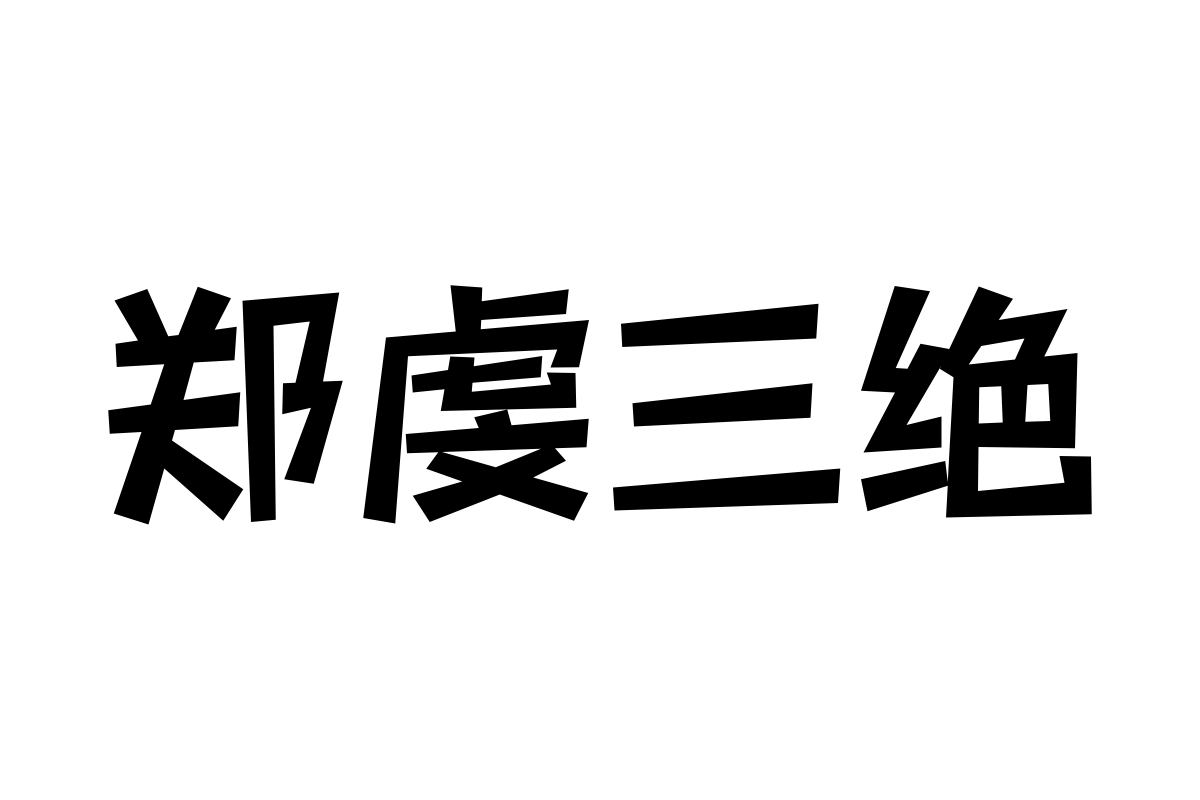
三极活力黑是一款专为中文用户设计的粗体字体,具有以下特点:
1. 字形饱满,笔画粗壮,给人一种强烈的视觉冲击力。
2. 结构紧凑,线条流畅,适合用于标题、广告等需要强调的文字。
3. 字体风格独特,具有较强的辨识度,易于识别和记忆。
4. 适用于各种场景,如网站、软件界面、广告牌等。
总之,三极活力黑是一款功能强大、适用范围广泛的粗体字体,能够满足用户在不同场景下的需求。